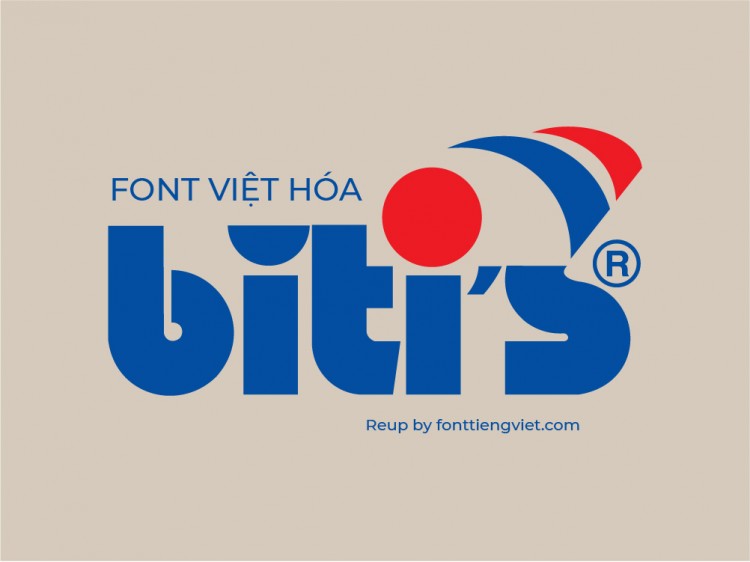
Khám phá sức mạnh của Font việt hóa UVN Bai Sau Nang dùng trong logo Bitis trong thiết kế thương hiệu
Lý do lựa chọn Font việt hóa UVN Bai Sau Nang dùng trong logo Bitis
Trong thế giới thiết kế đồ họa tại Việt Nam, việc tìm kiếm một bộ Font Chữ phù hợp để truyền tải bản sắc dân tộc là rất quan trọng. Font việt hóa UVN Bai Sau Nang dùng trong logo Bitis chính là một ví dụ điển hình cho sự kết hợp giữa tính thẩm mỹ và giá trị nhận diện. Đây là một phông chữ thuộc bộ UVN, được tinh chỉnh để phục vụ mục đích thiết kế chuyên nghiệp, đặc biệt là trong các dự án branding lớn.
Đặc điểm thiết kế của bộ font
Bộ font này sở hữu những đường nét dày dặn, vững chãi nhưng không kém phần mềm mại ở các góc cạnh. Khi ứng dụng Font việt hóa UVN Bai Sau Nang dùng trong logo Bitis, người thiết kế có thể tạo ra cảm giác tin cậy và bền bỉ. Điều này hoàn toàn phù hợp với tinh thần “Nâng niu bàn chân Việt” mà thương hiệu Bitis luôn hướng tới trong suốt nhiều thập kỷ qua.
Ứng dụng Font việt hóa UVN Bai Sau Nang dùng trong logo Bitis vào thực tế
Không chỉ giới hạn ở logo, phông chữ này còn được sử dụng rộng rãi trong các ấn phẩm truyền thông, bao bì sản phẩm và banner quảng cáo. Nhờ khả năng hiển thị tiếng Việt hoàn hảo, không lỗi dấu, nó giúp các bạn học sinh và sinh viên dễ dàng tiếp cận khi thực hiện bài tập thiết kế.
Cách tối ưu hóa font trong đồ họa
Để đạt hiệu quả cao nhất, bạn nên kết hợp font này với các tông màu tương phản mạnh. Việc sử dụng khoảng cách chữ hợp lý sẽ giúp thông điệp trở nên rõ ràng và ấn tượng hơn đối với người xem ngay từ cái nhìn đầu tiên.
Kết luận về bộ phông chữ ấn tượng